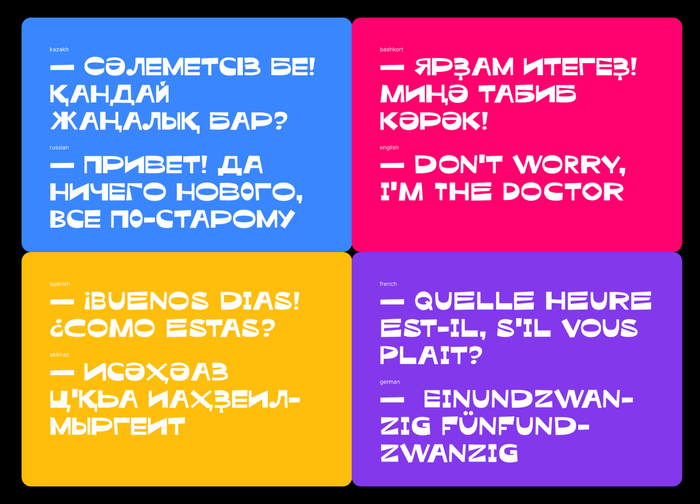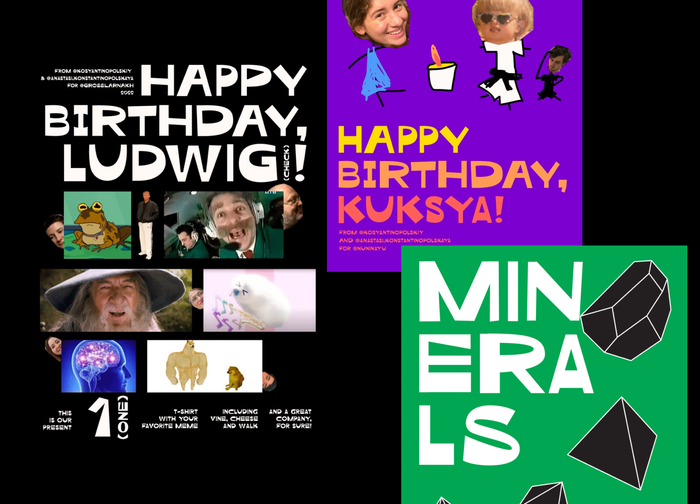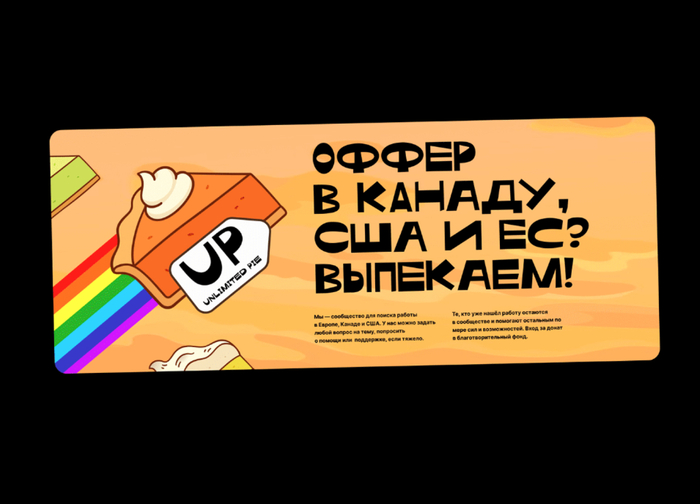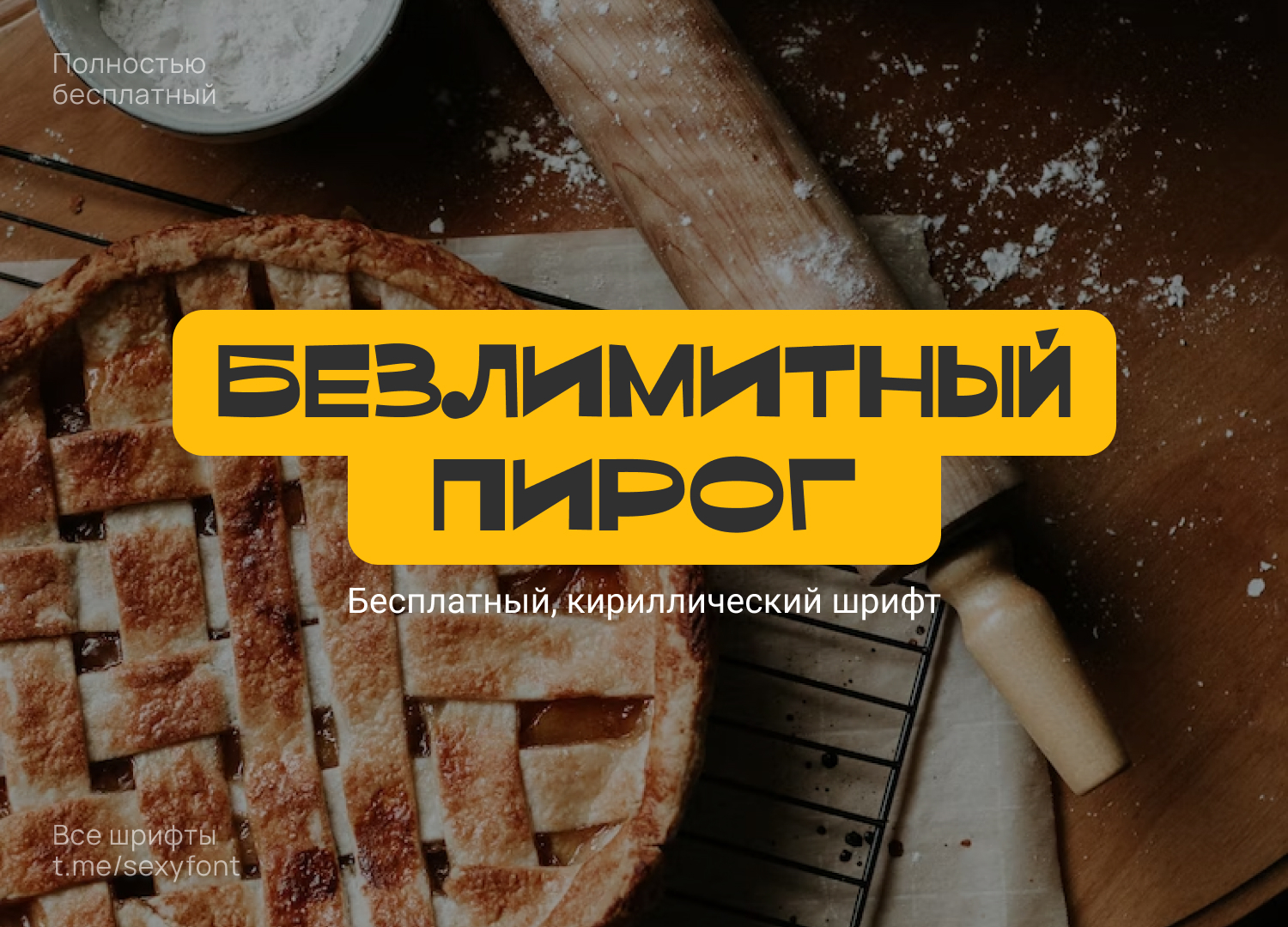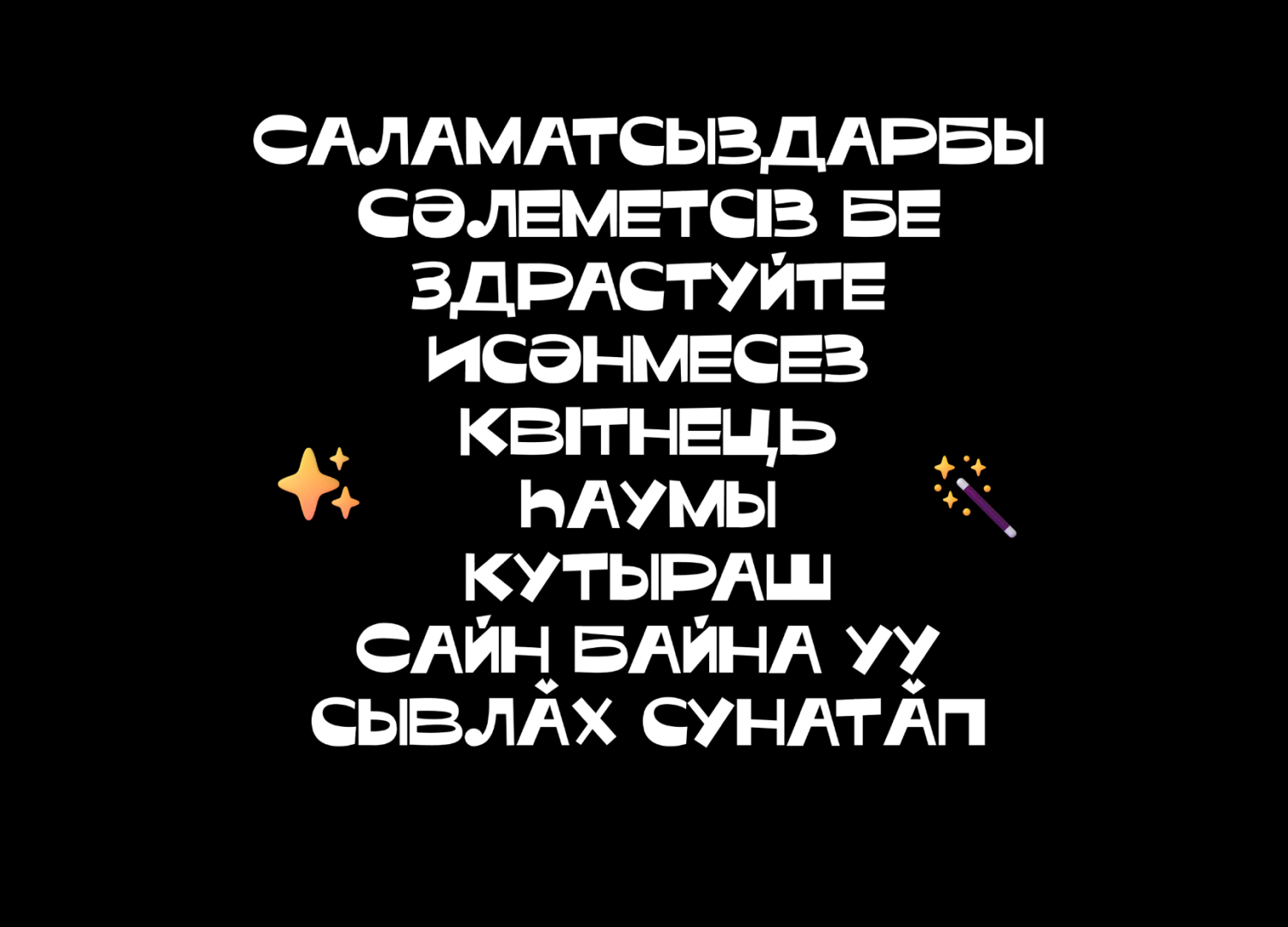
Кириллический шрифт пирог
Безлимитный пирог. Так называется наш следующий шрифт) Веселый, озорной. Поддерживает кучу языков. Мой родной – башкирский. А так же казахский, французский, испанский и т.д Бесплатно для личного и коммерческого использования. Автор: Екатерина Бакирова